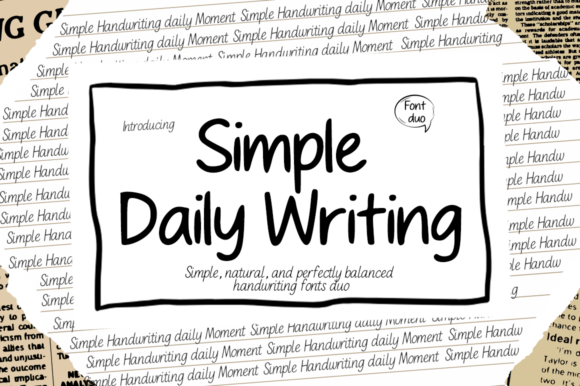
Simple Daily Writing
์ •๋ฐ€ํ•˜๊ฒŒ ์ œ์ž‘๋œ Simple Daily Writing๋Š” ๊น”๋”ํ•œ ๋ฒกํ„ฐ, ๋ถ€๋“œ๋Ÿฌ์šด ํƒ€์ดํฌ๊ทธ๋ž˜ํ”ผ ๋ฐ ์•ˆ์‹ฌํ•  ์ˆ˜ ์žˆ๋Š” ์ƒ์—…์šฉ ๋ผ์ด์„ ์Šค๋ฅผ ์ œ๊ณตํ•ฉ๋‹ˆ๋‹ค.